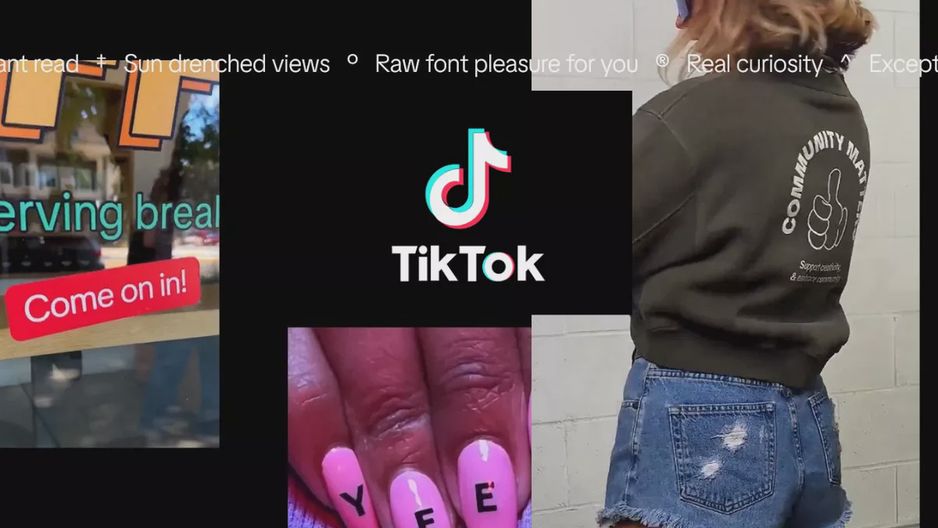
TikTok stworzył własny font. "Nie najgorętszy, ale sprawdzony"
Chiński serwis TikTok należący do ByteDance wprowadził na rynek własny font. Każdy może go pobrać za darmo i korzystać z niego do woli.
Dzięki temu użytkownicy czy też zaawansowani twórcy treści będą mogli zachować spójność w swoich pracach na różnych platformach. TikTok Sans, bo tak brzmi jego oficjalna nazwa, został „stworzony dla globalnej społeczności” - jak czytamy w poście w serwisie X - i „ma pomóc w tworzeniu wideo wysokiej jakości z sygnaturą rozpoznawalną dla TikToka”.
O opinię na temat TikTok Sans zapytaliśmy Łukasza Grondeckiego, CEO Page Interactive, eksperta UI/UX Design.
– Dobrze zaprojektowany font. Widać, że TikTok pomyślał o mobile i czytelności: są większe litery oraz dobry spacing – komentuje Grondecki – Co do trendów – geometric sans to bezpieczny wybór. Nie najgorętszy, ale sprawdzony. Dla brandów chcących wyglądać nowocześnie jest w porządku – ocenia.
Nasz ekspert porównuje też działanie TikToka do Apple.
– TikTok Sans to strategiczny ruch podobny do tego, co Apple zrobiło z San Francisco. Stworzenie spójnego ekosystemu typograficznego to już standard w big techach. Jako projektant doceniam szczególnie wsparcie dla ponad 460 języków i optymalizację pod mobile interface – dodaje Grondecki.